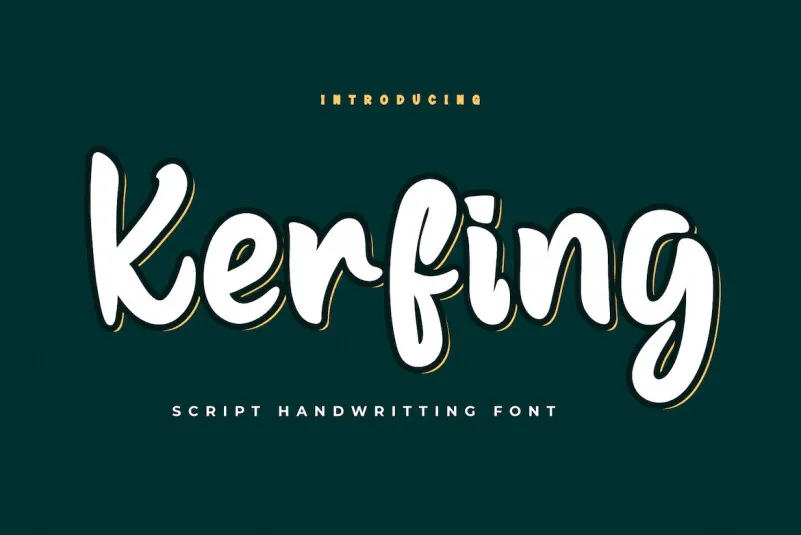
Esta é uma fonte criada através de uma delicada, mas linda e elegante mão do designer. Seu design é perfeito para quem busca estilos únicos para textos especiais e cabeçalhos em projetos de design especializados. Com sua graciosidade e sofisticação, essa font oferece um toque único que torna seus designs mais interessantes e memoráveis, adequados para uso em aplicativos variados. Ideal tanto para designers digitais quanto para profissionais de arte gráfica, a Kerfing Font é perfeita para aqueles buscando uma mão na obra cuidadosa e inspiradora. Para designers que buscam expressar suas ideias com um toque único, o designer productype trouxe essa fonte delicada e elegante, certificando-se de que seja usada no texto especial do seu próximo projeto ou cabeçalho. Sem dúvidas, a Kerfing Font é uma escolha segura para quem busca uma nova adição para seus projetos digitais.